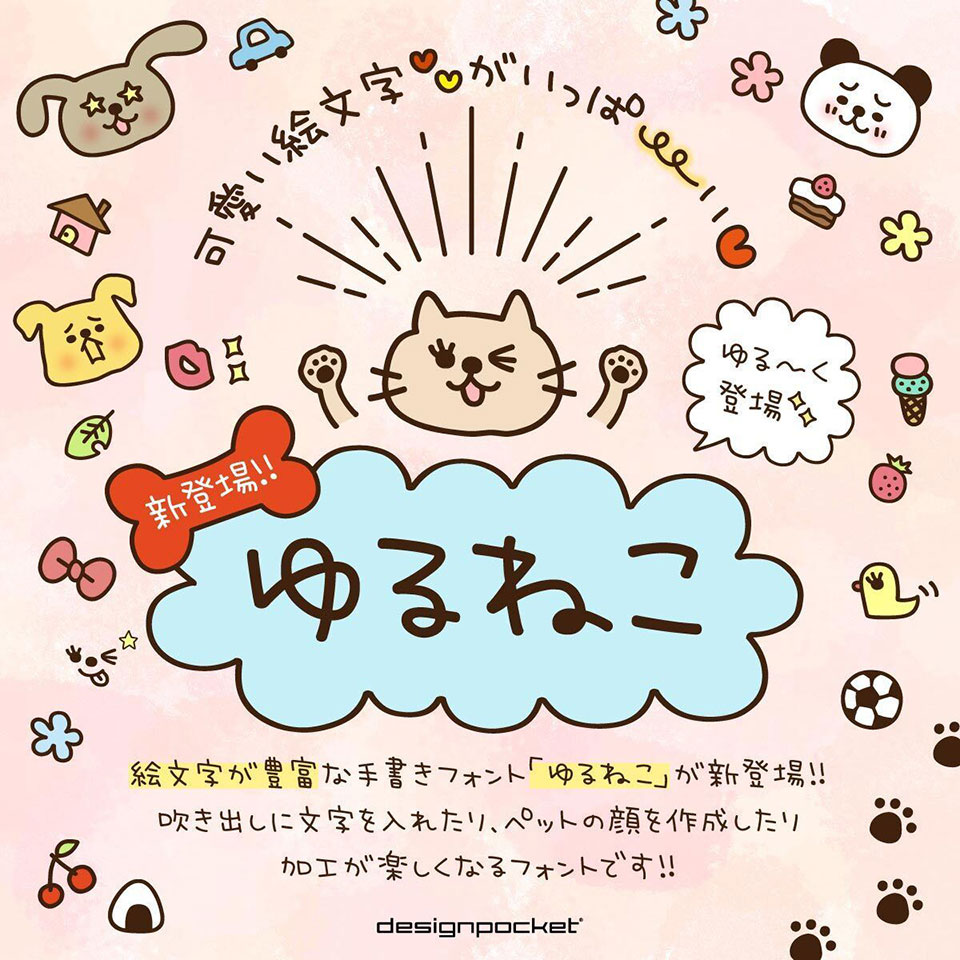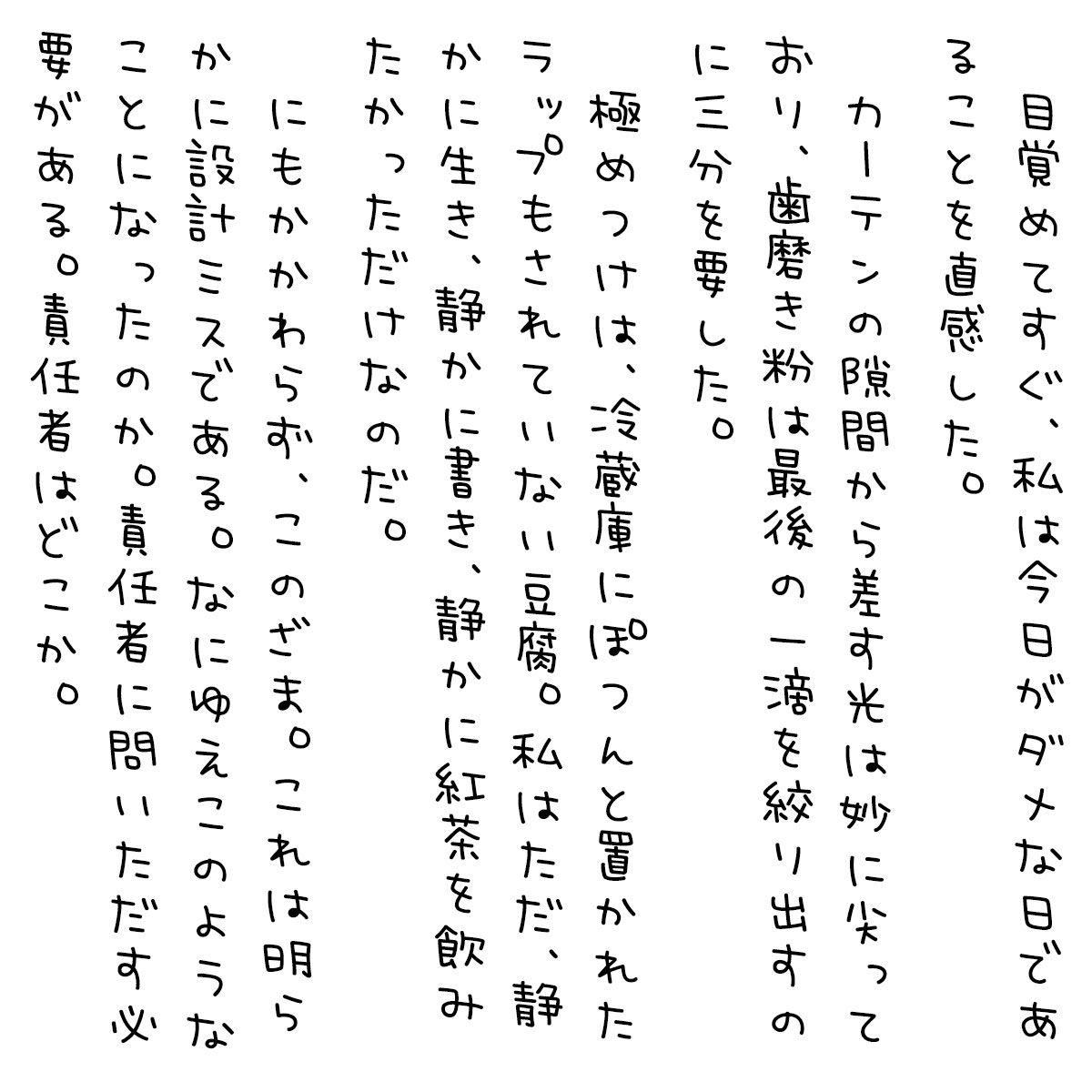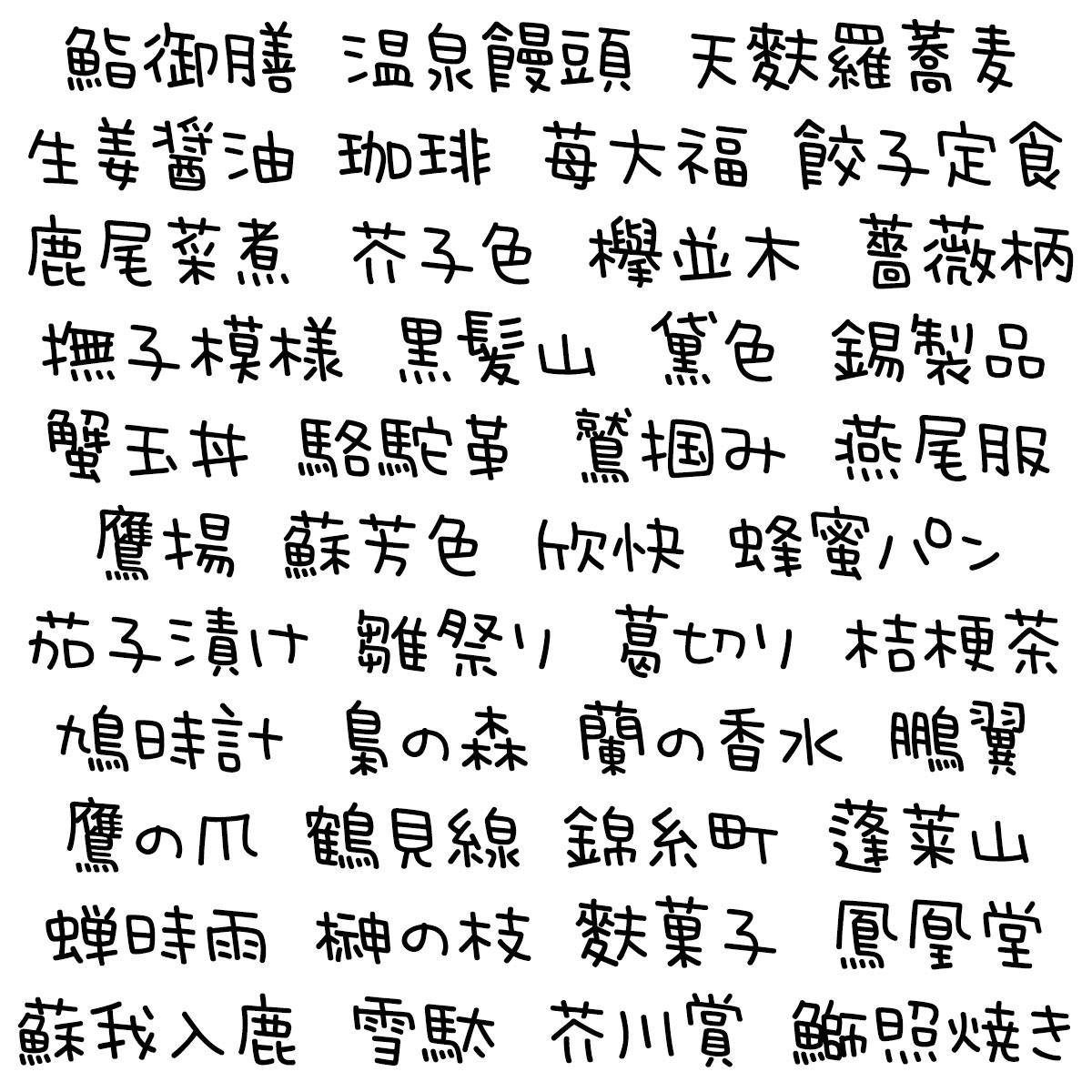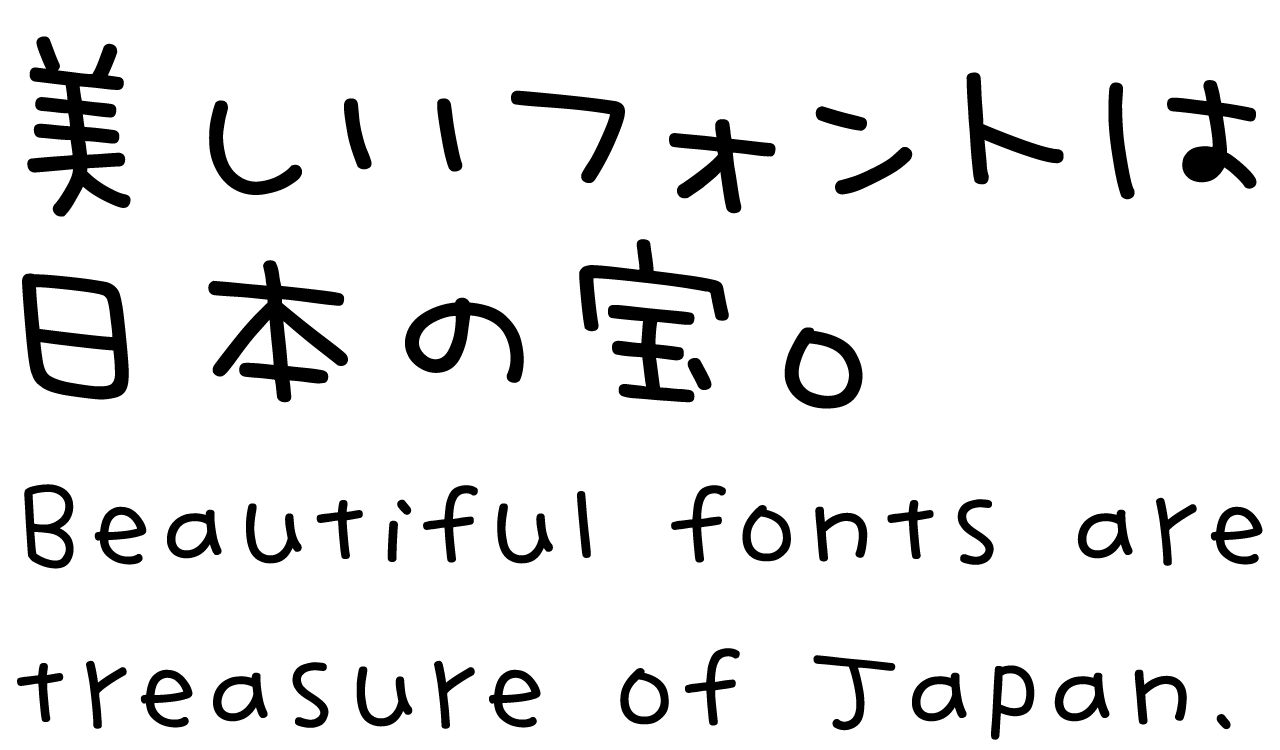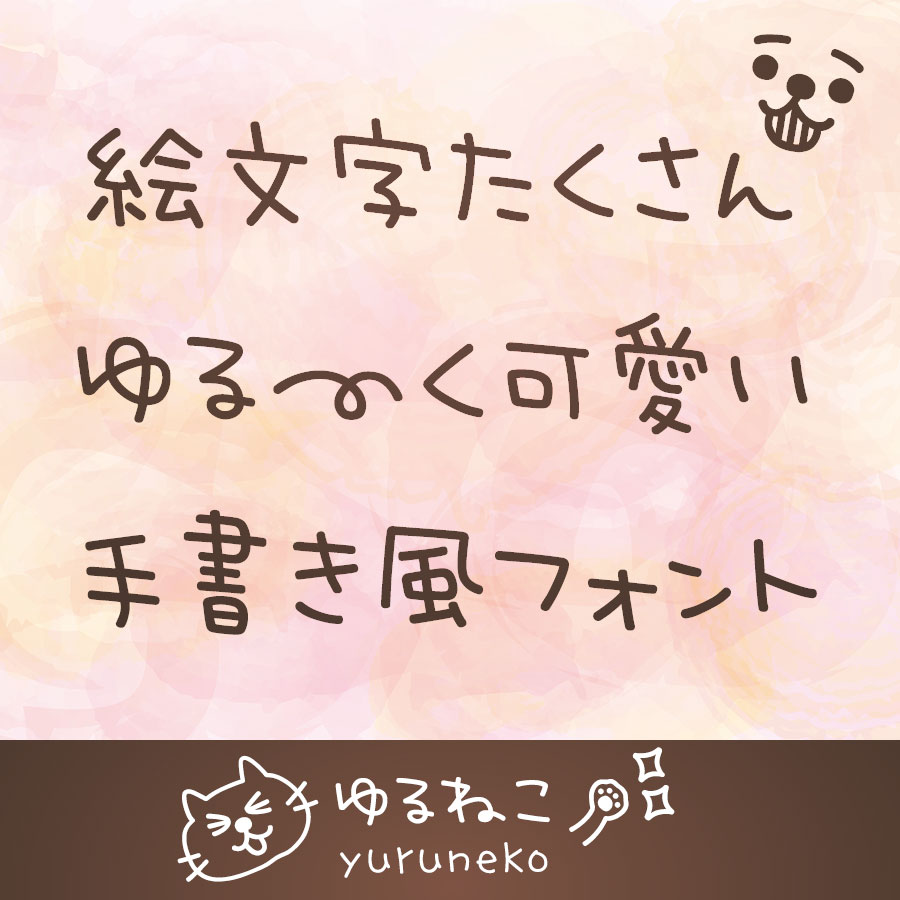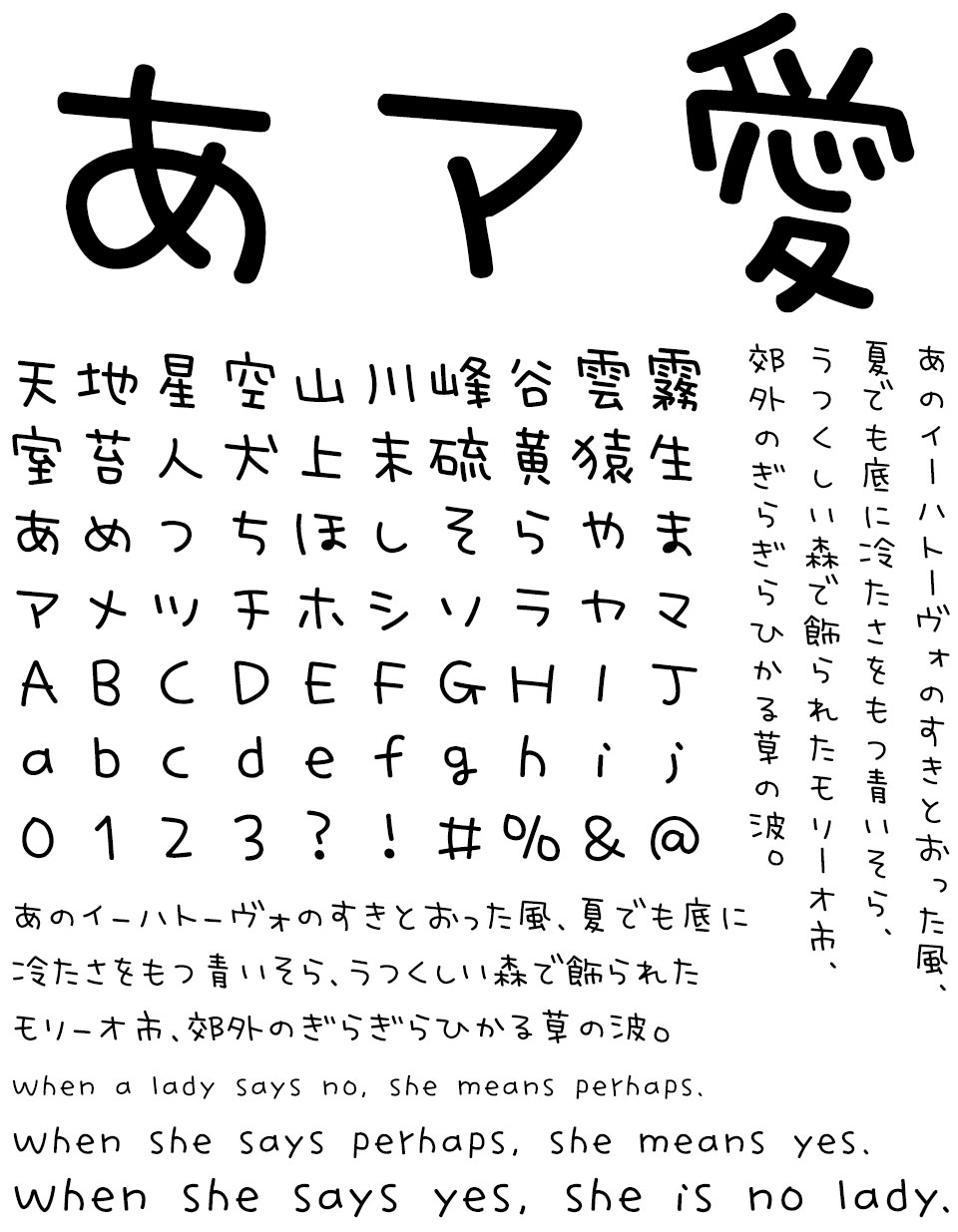
「ゆるねこ」は、手書きのあたたかさと遊び心をそのまま閉じ込めた、ふんわりやさしい手書き風フォントです。ひらがな・カタカナ・英数字・漢字(JIS第3水準)まで幅広く収録し、縦書き・横書きのどちらでも自然に使えるのが特長。
さらに、絵文字や吹き出しをたっぷり収録した「ゆるねこ-emoji」も同梱。SNS投稿やショップカード、メッセージカード、推し活グッズなど、「ちょっとかわいく伝えたい」シーンに寄り添います。
ゆるねこ
「ゆるねこ」とは?
「ゆるねこ」が生まれるまでの歩みと作者のストーリー
「ゆるねこ」の作者ゆるねこさん作のイラスト
<「ゆるねこ」の作者ゆるねこさん作のイラスト>
「ゆるねこ」は、作者自身が長年愛してきた 手書きの温かさ と 猫への深い愛情 から生まれたフォントです。2004年からコツコツと積み重ねてきたフォント制作の経験をもとに、一度お休みした時期を経て、2025年に新たな気持ちで再スタート。かわいさとゆるさのバランス、自然体の脱力感、そして遊べる絵文字たち。作者の人生や大切なルーツが散りばめられたこの あたたかい手書きフォント です。
制作者ご本人の言葉で、その原点、フォントづくりを始めたきっかけ、現在の活動、そして“ゆるねこ”に込めたこだわりを紹介します。
猫とアートに囲まれた創作ルーツ
ゆるねこフォントの作者ゆるねこさんの愛猫達
<ゆるねこさんとともに暮らす愛猫達>
まずはご挨拶と、猫との暮らし
はじめまして。ゆるねこと申します。
名前の通り猫が大好きで、現在まで沢山の猫を保護し暮らしてきた愛猫家です。
学生時代の美術経験と好きな科目
学生時代は美術部で水彩画・油絵を描き、絵画・毛筆・硬筆ではコンクールに出品し賞をもらっていました。手先を使う作業が好きで今の活動にも活かせている気がします。
美術・音楽・体育が好きでしたが、理数はめっちゃ苦手でした…。記号や数字を見るとめまいがします(笑)
家庭環境と音楽活動のルーツ
ギター流しをしていた両親の元で育ち、小さな頃から演歌を仕込まれ、20代の頃はバンド活動に明け暮れプロ活動していた時期があります。
現在も某アプリにて歌活中です♪歌ではROCKしていますが、可愛いものが大好きで見るとテンションが上がります。
WEBや動画制作と、フォント制作へのつながり
友人のお店のWEBをデザインしたり、最近では歌イベントの告知動画を作ったりもしました。
構想を練って作り上げる事にやりがいを感じていて、これはフォント制作にも通ずるものがあると思います。
温かさが伝わる手書きの文字が昔から大好きでした。
フォントはガールズ系の可愛いものを中心に制作しています。
フォント制作を始めたきっかけと初期の活動
ゆるねこフォントづくりを応援する猫達
<フォントづくりを応援する猫達>
ブログから始まったフォントづくり
私がフォントを知ったのは2004年で、フォントを作り始めたのも2004年です。
当時、猫とDIYのブログを書いていて、ただ画像を載せるだけでは味気ない気がして、イラストや画像に文字入れしたら可愛いだろうなと思い作り始めたのがきっかけです。
自分で手書きをすると、その日の体調で字体が変わってしまい上手く書けない事もあります。
そんな悩みもカバーしてくれる便利な手書きフォントです♪
常に猫達に邪魔(手伝い?)をされながらフォント制作してきました。
ゆるねこフォントづくりを時に邪魔する猫達
<フォントづくりを時に邪魔する猫達>
友人フォント制作で実感した、地道な作業
依頼があり友人の手書きフォントを作った時には、1文字1文字紙に書かれたものをスキャンしてフォント化しました。
フォント作りは地道で時間のかかる作業だと改めて思いました。
友人からの依頼でフォント制作した際の原稿
<友人からの依頼で制作した際の原稿>
個人サイトでの配布と、多くの利用者
2005年頃から個人サイトでフォントの配布をはじめました。
サイトは細々ですが2020年頃まで続き、企業様はじめ1200人程の方にフォントを使用していただきました。
多忙によりサイトは閉鎖をしたのですが、作りかけのままになっているフォントもあるのがずっと気がかりでした。
サイト閉鎖から、2025年の再始動へ
またフォントを作ろうと2025年に再始動。
デザインポケットさんに委託販売をお願いする形で再始動が叶いました。
「ゆるねこ」誕生とフォント制作の再スタート
手書き書体「ゆるねこ」を公開
2025年、JIS第3水準漢字まで収録のゆる可愛い手書き書体「ゆるねこ」を公開しました。
以前に公開していた書体を元に1から作り直し、書体名も変えパワーアップしています。
フォント作りを再始動出来た時には、フォント名は「ゆるねこ」にしようと決めていました。
本業と並行した、ゆるやかな制作スタイル
現在は、本業の傍ら隙間時間でフォント制作をしています。
名前の通り活動もゆるいのですが、これから可愛くて使いやすいフォントを公開していけたらと思っていますのでよろしくお願いします!
ゆるねこさんが新たなフォントの制作に取り組む様子
<新たなフォントの制作に取り組む様子>
「ゆるねこ」制作で大切にしているこだわり
ゆるさと可愛さ、自然な脱力感
可愛さを重視しつつゆるさも出るように、自然な脱力感を意識して作りました。
文章を見て癒されたり、手作り感が出せたら嬉しいです。
絵文字・吹き出しで“遊べるフォント”に
ゆるねこは絵文字や吹き出しの収録が豊富です。
絵文字を好きなように組み合わせてペットの沢山の表情が作れる「遊べるフォント」です。文章と絵文字を組み合わせて可愛い画像が作れるような工夫をしました。
デザインポケットのデザイナーさんが作ってくださった紹介画像がめちゃくちゃ可愛くてお気に入りです♪
デザインポケット作 ゆるねこフォントの紹介画像
<デザインポケット作 ゆるねこフォントの紹介画像>
今後の制作活動について
ゆるねこさんの制作中の次回作
<制作中の次回作>
次回作に向けたフォント制作
ゆるねこを公開し、次作品も着々と進めています♪
今後公開したいと思っている作りかけのフォントは5書体ほどあります。こういうフォントが作りたい!という構想は山ほどあるのですが、時間が足りなすぎてつらいです…笑
ゆるやかな制作ペースと、読者へのメッセージ
フォント作りを5年ぶりに再開し、再始動してから作り直しているのでゆるゆる時間がかかりますが、気長にお付き合いいただけましたら幸いです。
次回作の制作も応援するゆるねこ家の猫達
<これまでも、これからも制作も応援する猫達>
「ゆるねこ」の特徴
ふんわり手書きでやさしい雰囲気
ふんわり手書きでやさしい雰囲気 ゆるねこ フォント
やわらかな丸みと、ほどよく太めの線が印象的な「ゆるねこ」。
素朴な手書きのぬくもりをそのままに、バランスよく整った字形で読みやすさも両立しています。縦書き・横書きのどちらでも自然に馴染むため、手紙風デザインやメッセージカードにも最適。
SNSのテキストやショップカードなど、「やさしく伝えたい」シーンにぴったりです。
絵文字・吹き出しも使える「2スタイル構成」
絵文字・吹き出しも使える「2スタイル構成」 ゆるねこ フォント
「ゆるねこ」には、基本の 「ゆるねこ.ttf」と絵文字・吹き出し・マークをたっぷり収録した 「ゆるねこ-emoji.ttf」の2つのスタイルが同梱されています。
ひと言コメントはベーシックな「ゆるねこ.ttf」で、にぎやかに見せたいところは「ゆるねこ-emoji.ttf」で。文字とデコレーションをシーンに合わせて使い分けられる、遊べる手書きフォントです。
たっぷり安心の幅広い文字セット
幅広い文字セットで名前や地名にも安心 ゆるねこ フォント
かわいい見た目だけでなく、JIS第3水準までの漢字に対応しているのも大きな特長です。
ひらがな・カタカナ・英数字・記号に加え、一般的な手書きフォントでは表示できないことの多い漢字までカバー。
縦書きの文章でもバランスよく
縦書きの文章でもバランスよく ゆるねこ フォント
縦書きの文章でもバランスよく表示されるため、手紙風レイアウトや案内文などにも活用できます。
< ゆるねこ 文字サンプル >
< ゆるねこ-emoji 収録絵文字 >